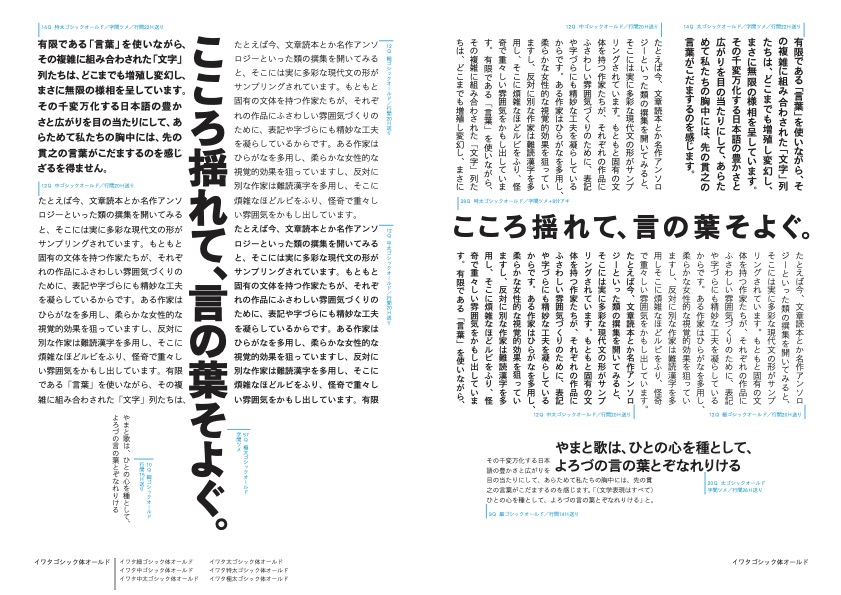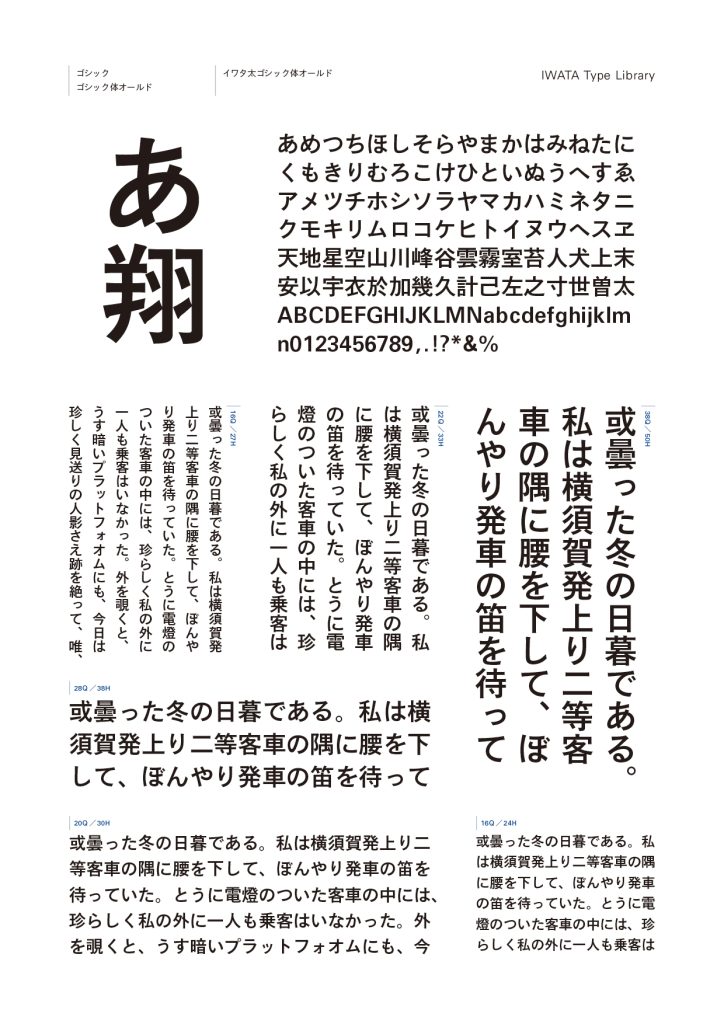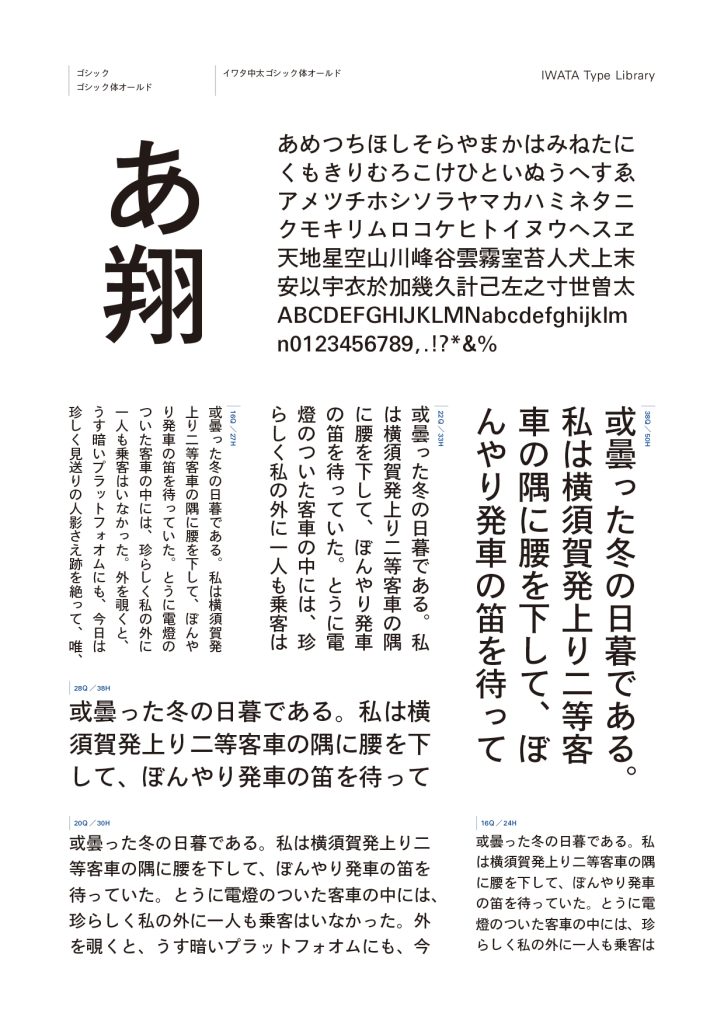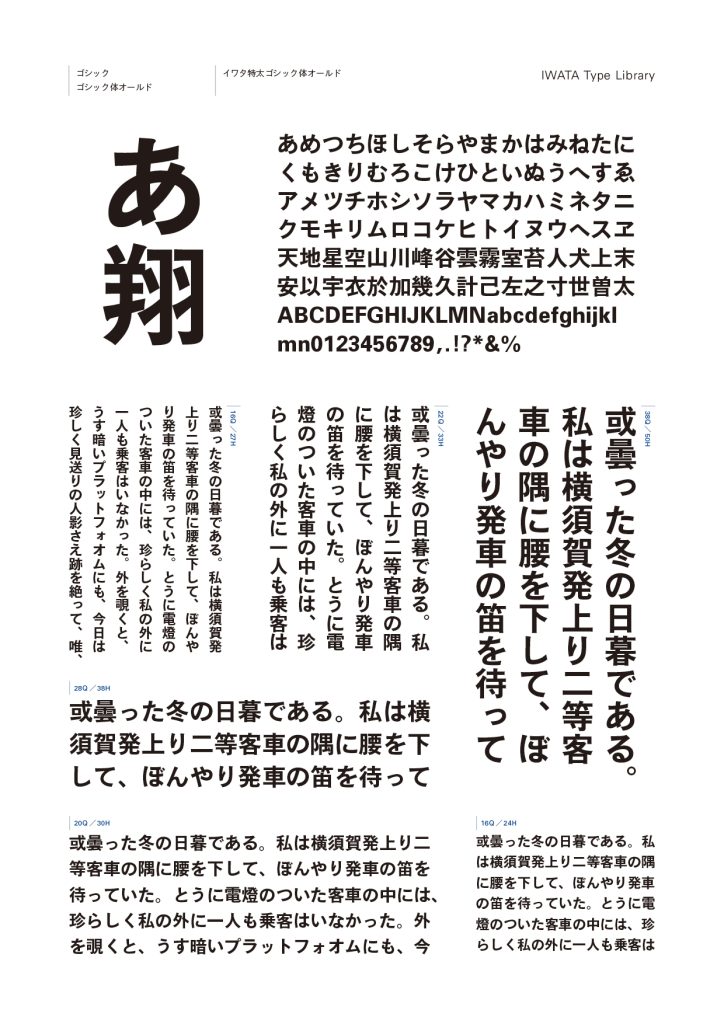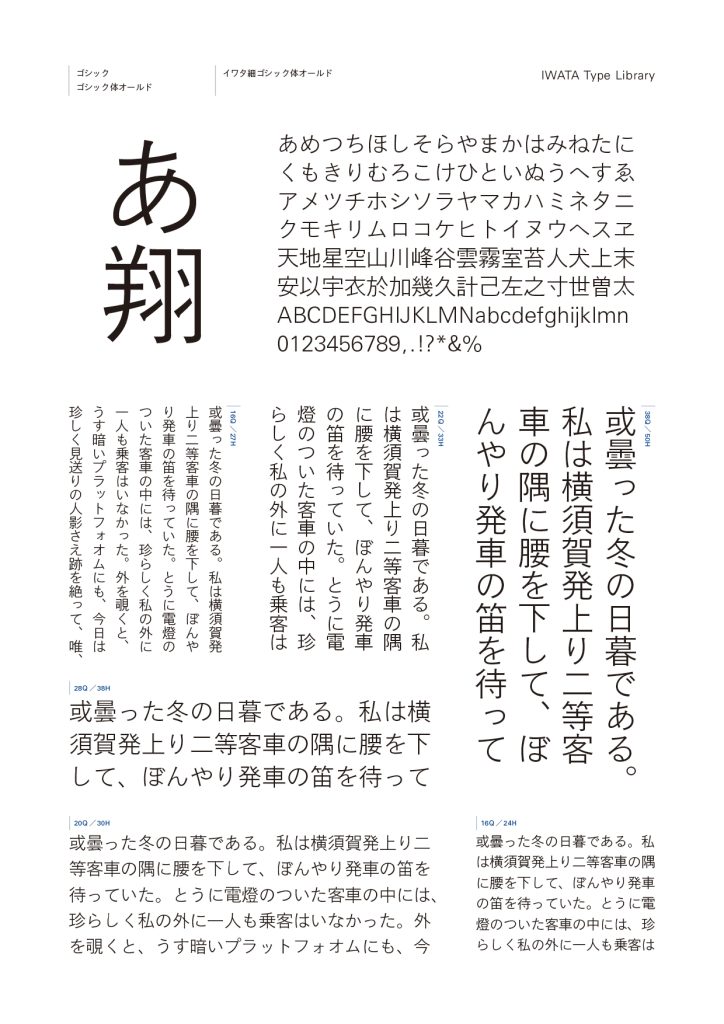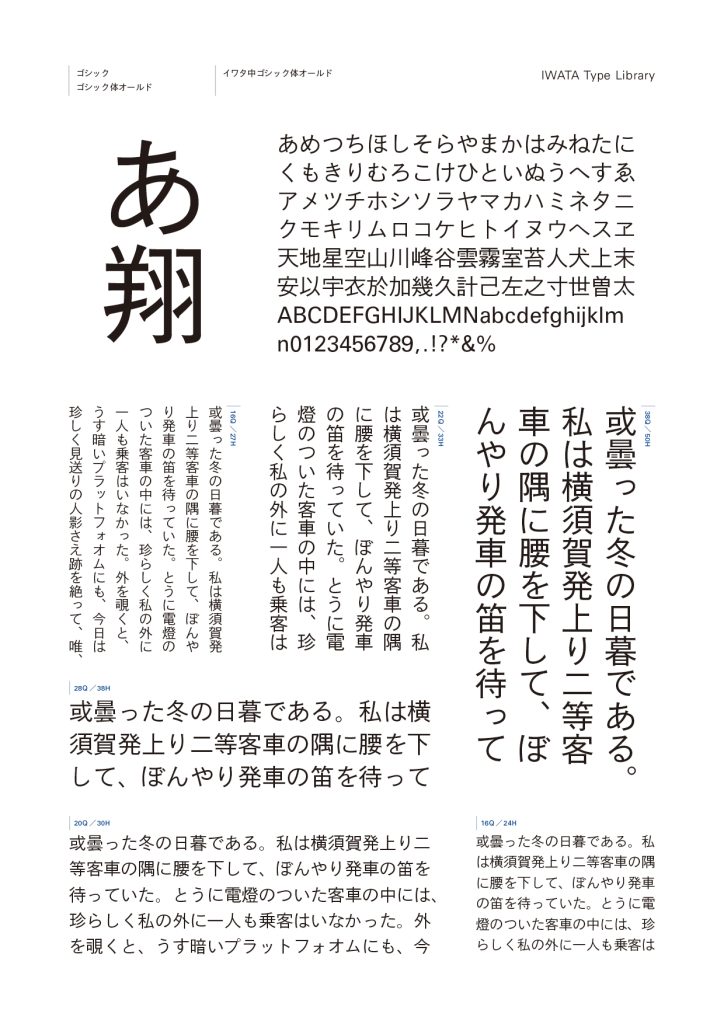
ゴシック体オールド
活字風のシャープで力強いデザインを持ちながら、柔らかさも兼ね備えたオールドスタイルのゴシック体です。
起筆・終筆部にアクセントを持たせ、クラシックな雰囲気は「イワタ明朝体オールド」との親和性が高く、組み合わせて使用することで統一感のある美しいデザインが可能です。ウェイトは「細」から「極太」までの6種類を揃え、大見出しから本文まで幅広い用途に対応できる書体です。